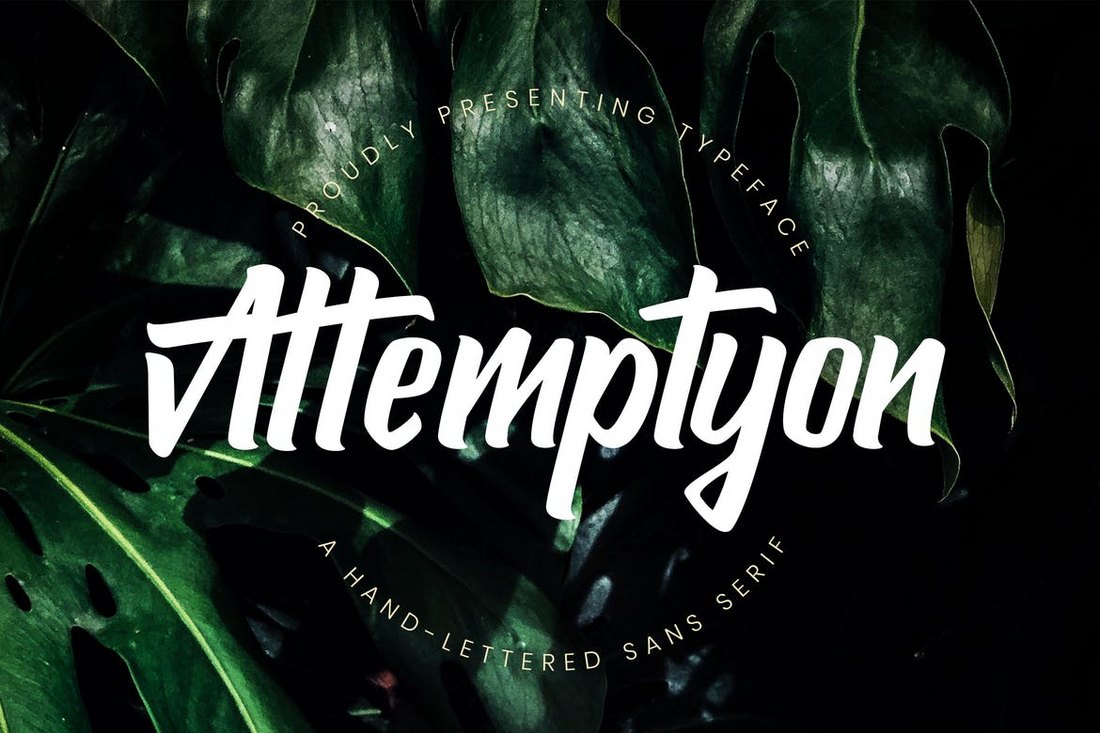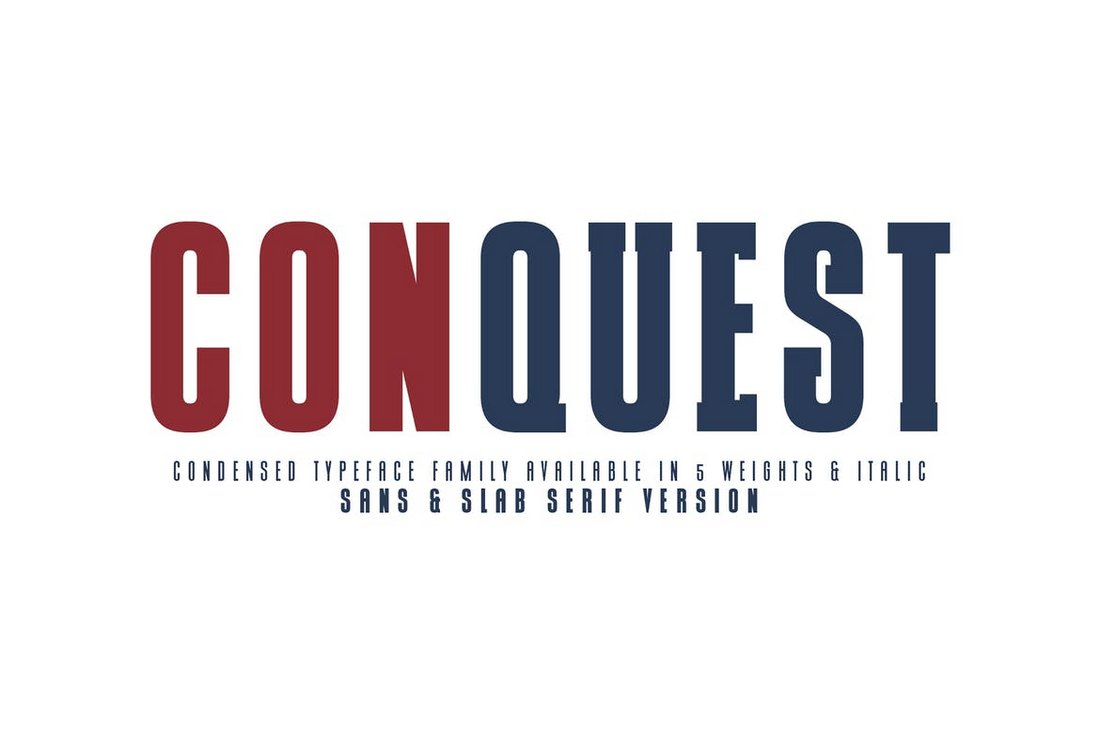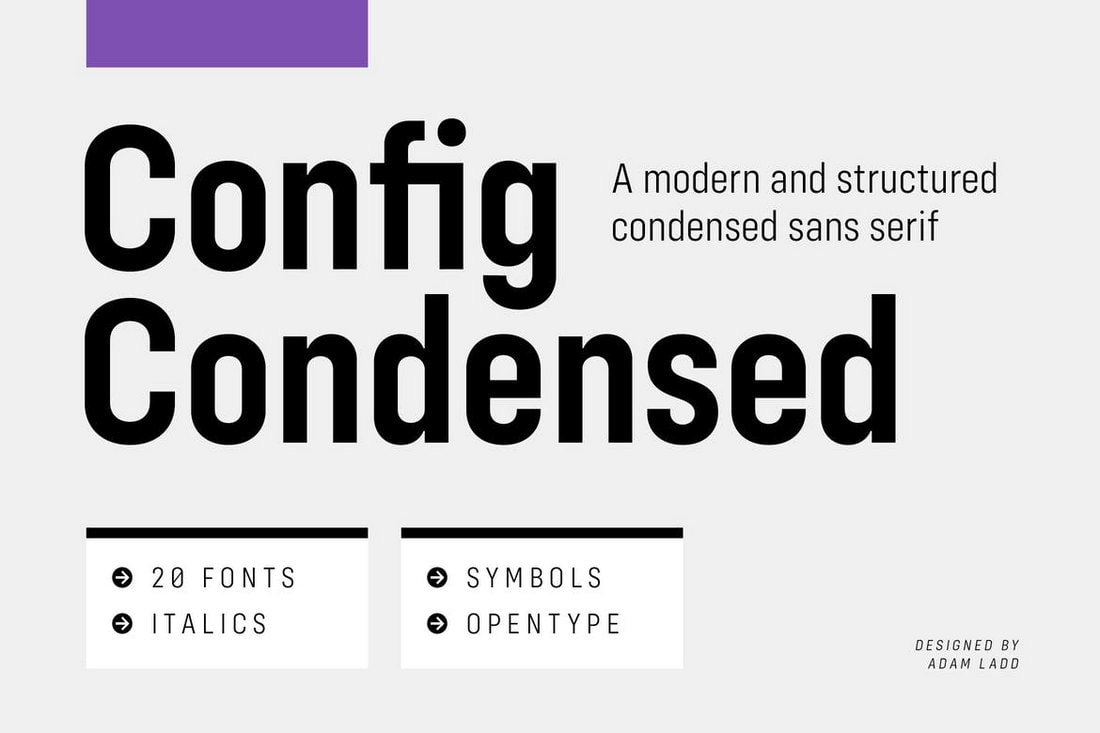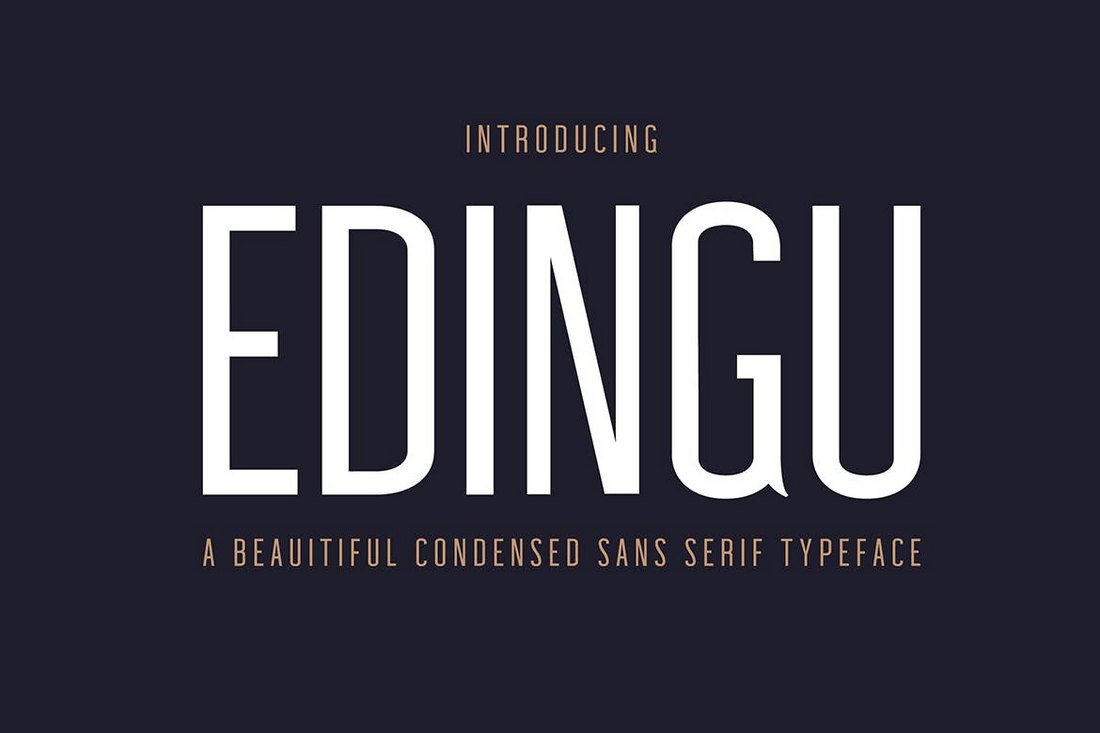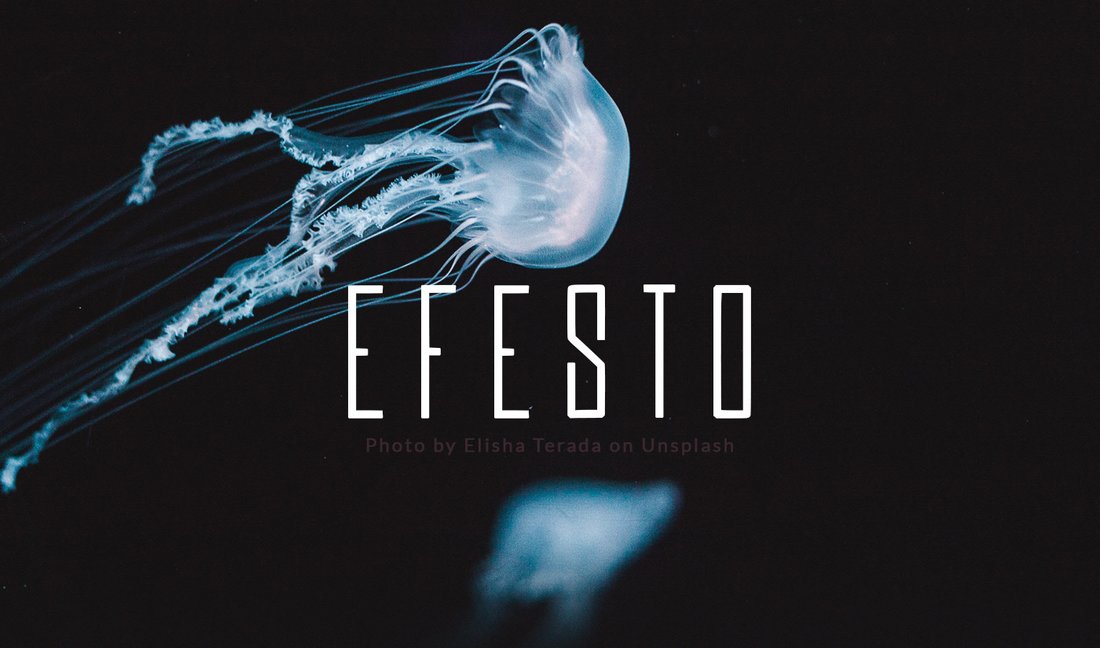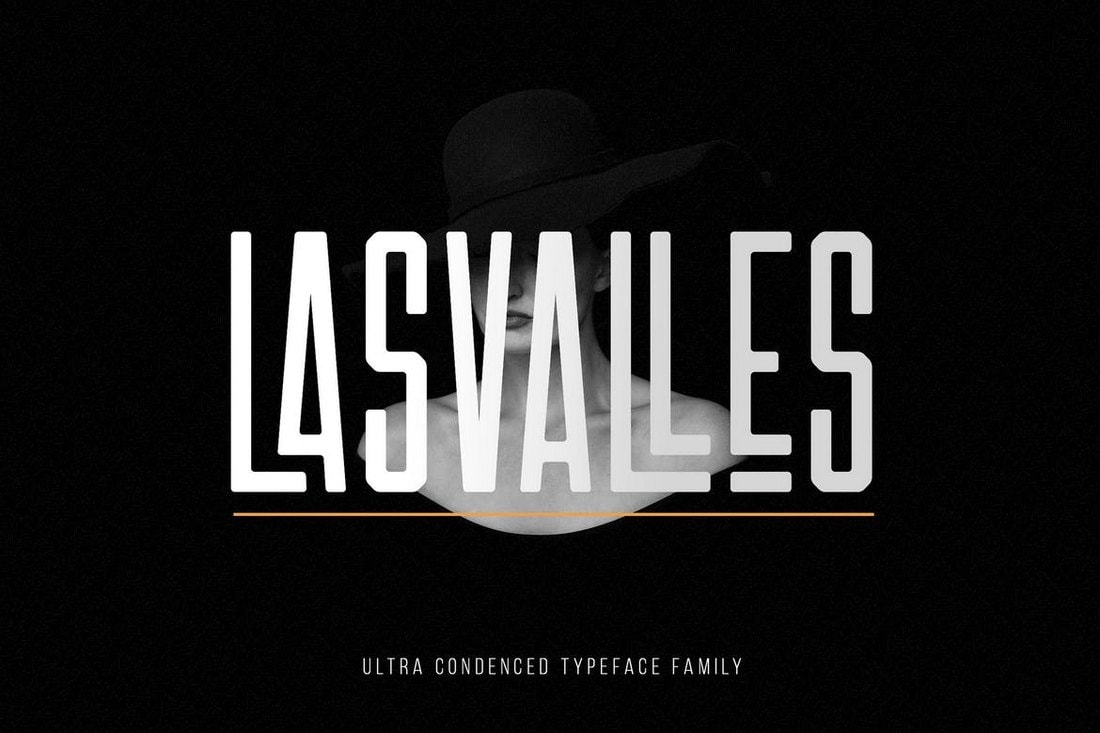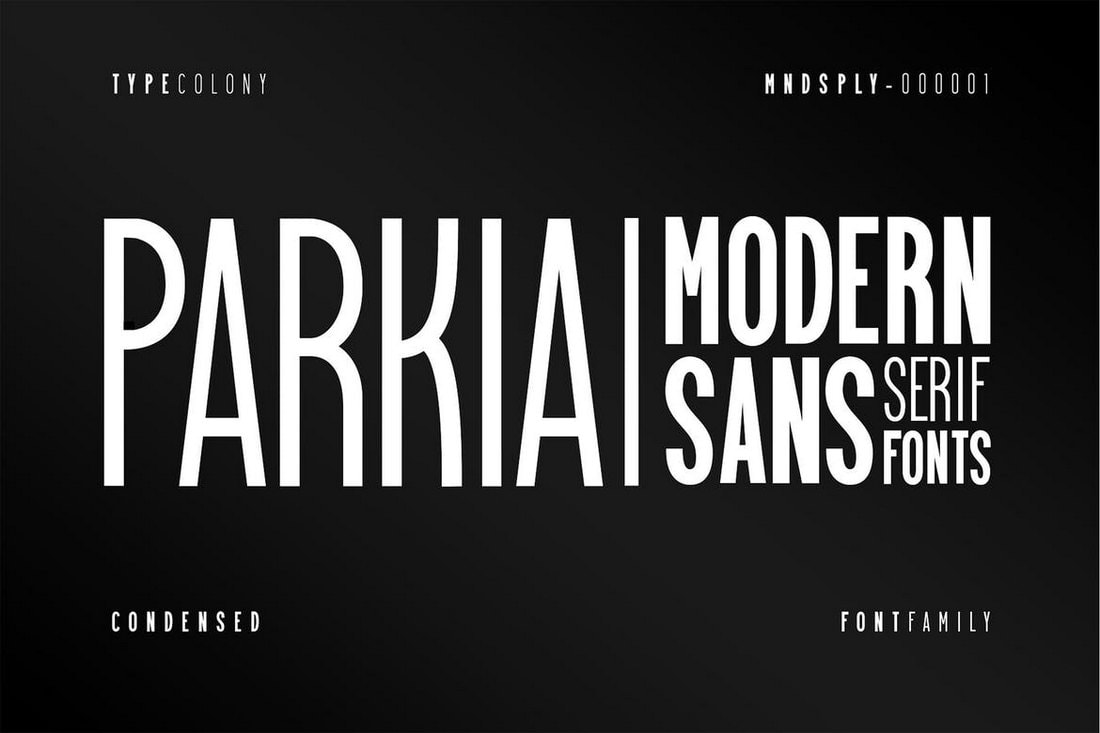
與目前主流的認(rèn)識(shí)相反,經(jīng)過(guò)壓縮處理和縮小寬度的窄字體不會(huì)使你的文本信息在排版和識(shí)別上變得擁擠。 你只需知道使用該字體的適當(dāng)時(shí)間和位置。 如今,窄字體被廣泛用于標(biāo)題和需要吸引注意力的文本消息中,當(dāng)在正確的位置使用它們時(shí),它們可以產(chǎn)生驚人的影響!
當(dāng)然,對(duì)于項(xiàng)目來(lái)說(shuō),尤其是網(wǎng)站設(shè)計(jì)以及平面類(lèi)設(shè)計(jì)的項(xiàng)目來(lái)說(shuō),字體的選用需要進(jìn)行大量的測(cè)試和實(shí)驗(yàn)才能找到適合設(shè)計(jì)的完美字體,我們希望在我們選擇的這些精簡(jiǎn)和風(fēng)格各異的窄字體中有你目前需要的資源,并可以幫助你獲得良好的開(kāi)端!
什么是Condensed或Narrow字體?(What is a Condensed or Narrow Font?)
經(jīng)過(guò)壓縮處理和縮小寬度的字體,一般是指在高度或?qū)挾壬辖?jīng)過(guò)處理的字符設(shè)計(jì)。 字體在字符之間的空間也比常規(guī)字體窄得多。
雖然許多設(shè)計(jì)師建議不要在正文中使用這種字體類(lèi)型,但這些字體在設(shè)計(jì)大型標(biāo)題時(shí)是一種流行的選擇,特別是在海報(bào),網(wǎng)頁(yè)設(shè)計(jì)中的標(biāo)題,主視覺(jué)圖甚至?xí)饷婧兔小?/p>
1.Config Condensed – Modern Font Family
Config提供了一系列濃縮風(fēng)格的字體,具有專(zhuān)業(yè)的無(wú)襯線設(shè)計(jì)。 它包括20種不同的字體,可以用于許多不同類(lèi)型的設(shè)計(jì),包括標(biāo)題和正文。
2.Edingu – Condensed Sans Serif Font Family
Edingu是一款優(yōu)雅的字體,采用現(xiàn)代設(shè)計(jì),是專(zhuān)業(yè),奢華和品牌設(shè)計(jì)的理想選擇。 該字體有3種不同的樣式,包括常規(guī)樣式,圓形樣式和斜體樣式。
3.CONQUEST – Sans & Slab Serif Font
Conquest是一種大膽的襯線字體,在字體寬度的設(shè)計(jì)上,壓縮處理的并不明顯。 它最適合用于制作與體育和娛樂(lè)品牌相關(guān)的標(biāo)題。 該字體也有sans-serif和slab serif格式設(shè)計(jì)。
4.Story Telling – Fun Condensed Font
這種有趣而古怪的濃縮字體是制作海報(bào),賀卡,書(shū)籍封面以及與所有特定年齡段兒童相關(guān)的設(shè)計(jì)的絕佳選擇。 字體包括連字以及不同字形等等。
5.Genuine – Free Condensed Font
6.Efesto – Free Modern Narrow Font
7.Parkia – Condensed Typeface
Parkia提供了一系列精簡(jiǎn)的字體,包括各種樣式和字體粗細(xì)。 你可以將此字體用于不同類(lèi)型的專(zhuān)業(yè)和創(chuàng)意項(xiàng)目以及打印設(shè)計(jì)中。
8.Las Valles – Ultra Condensed Fonts
這種優(yōu)雅和精簡(jiǎn)的字體是奢侈品和高端品牌設(shè)計(jì)logo,網(wǎng)站設(shè)計(jì)標(biāo)題和傳單的絕佳選擇。 字體包括全部大寫(xiě)字母以及標(biāo)點(diǎn)符號(hào)和數(shù)字。
9.Sprout – Narrow Sans Serif Font
Sprout具有高而窄的設(shè)計(jì),使其成為制作各種設(shè)計(jì)的絕佳字體,包括賀卡,網(wǎng)站標(biāo)題,海報(bào),社交媒體帖等等。
10.Attemptyon – Modern Sans Serif Typeface
Attemptyon是一種現(xiàn)代字體,具有狹窄的設(shè)計(jì)和腳本風(fēng)格。 該字體最適合品牌,包裝和標(biāo)簽設(shè)計(jì)。 它還包括字形,連字和Web字體。
總結(jié)
這是我們的一系列美麗,鼓舞人心的字體和字體集合。 我們希望文章中分享的這些具有大膽和創(chuàng)意設(shè)計(jì)的字體可以滿足你不管是海報(bào)設(shè)計(jì),網(wǎng)頁(yè)設(shè)計(jì)以及其他設(shè)計(jì)類(lèi)型項(xiàng)目的各種需求! 希望你能夠找到適合于你的項(xiàng)目的合適的字體,并通過(guò)該字體為你的項(xiàng)目提供更好的視覺(jué)體驗(yàn)。